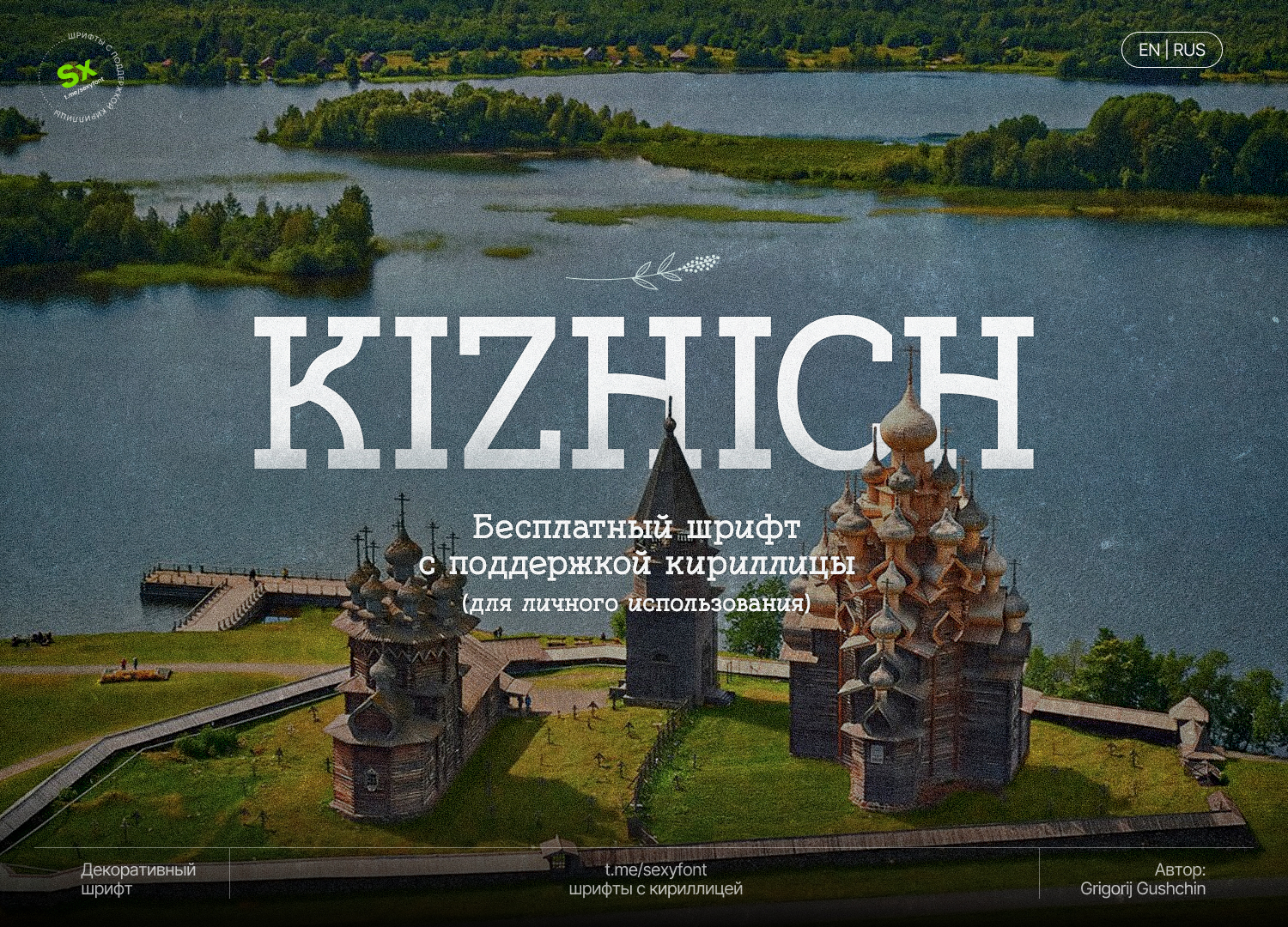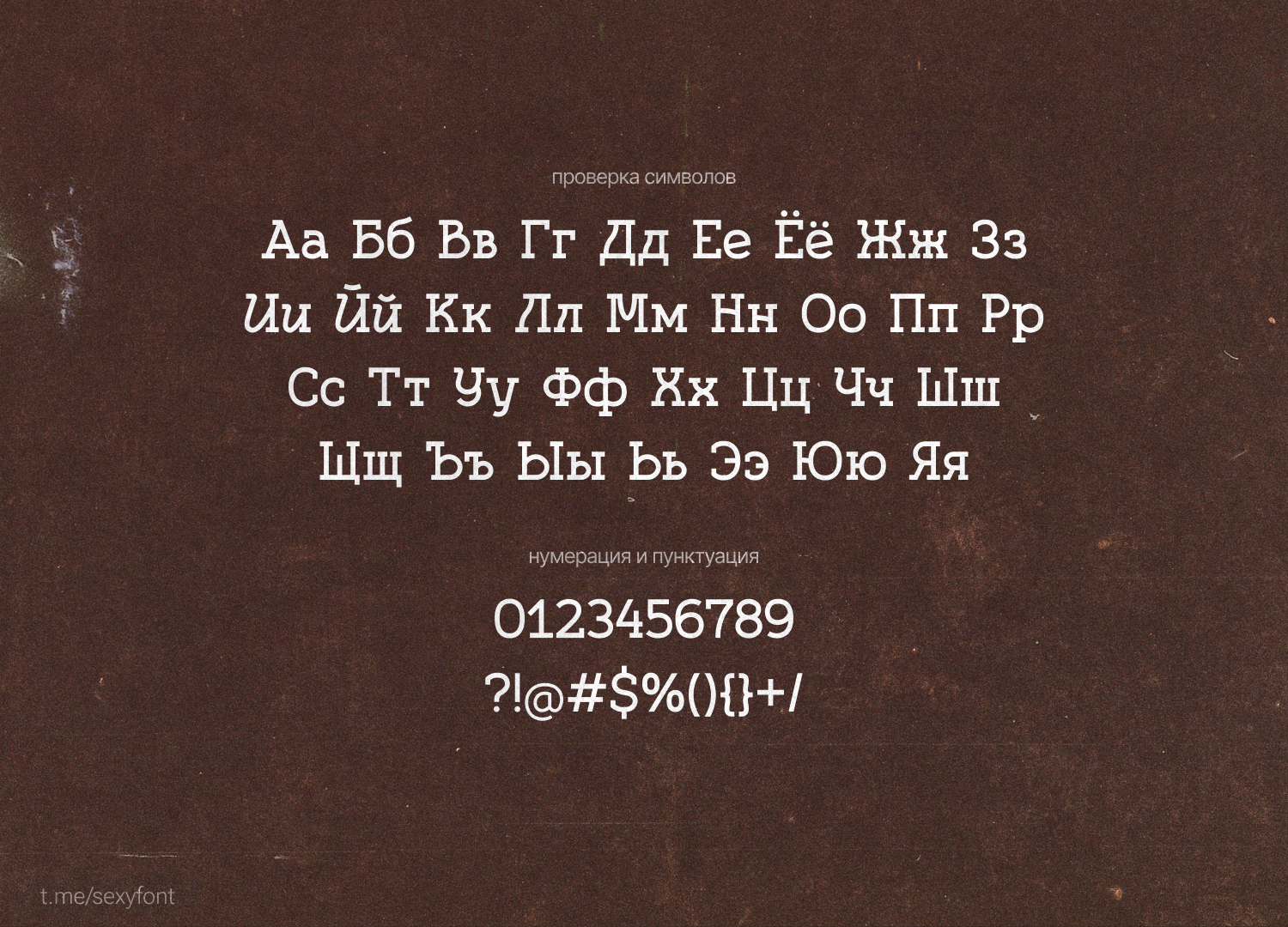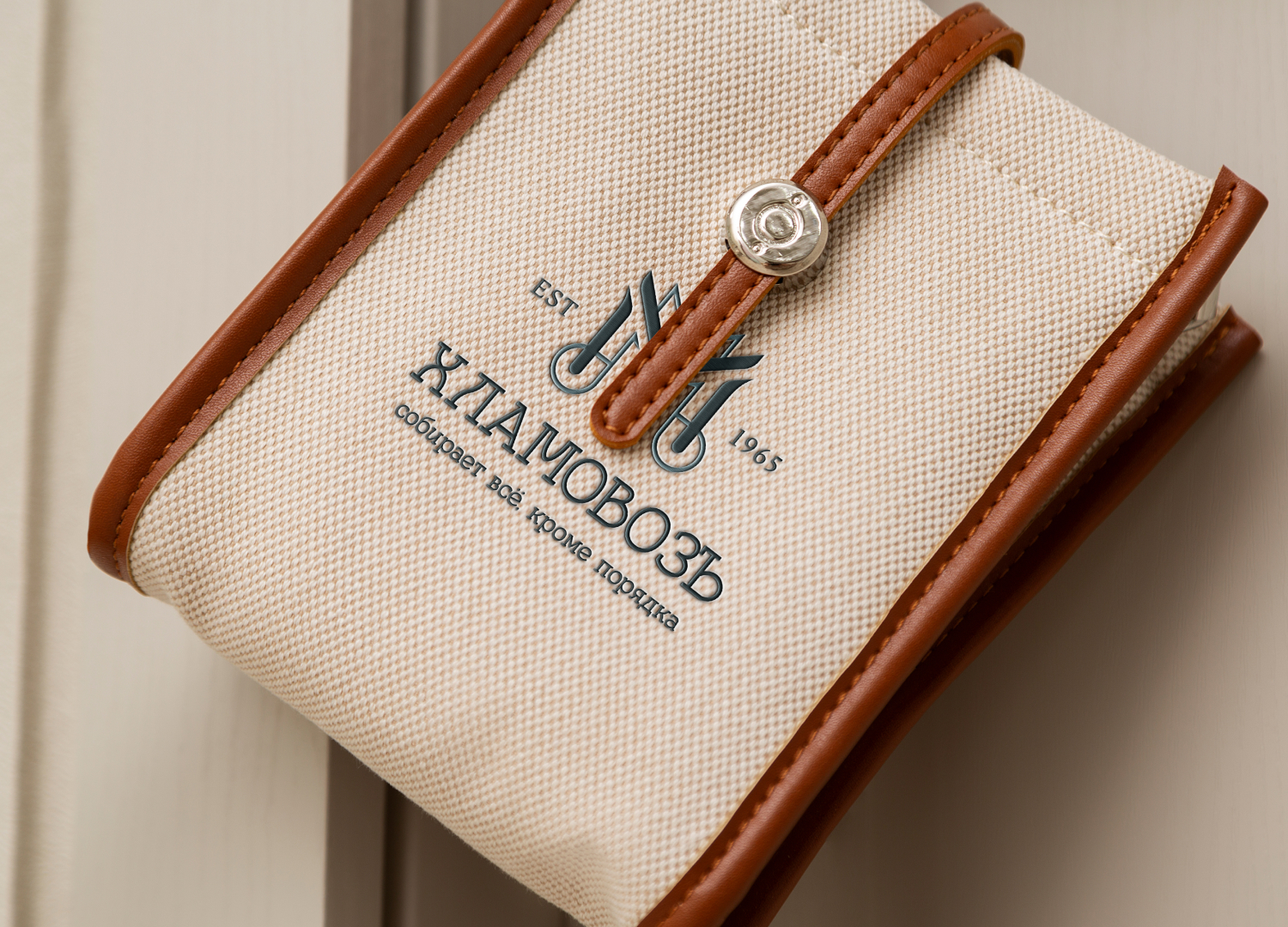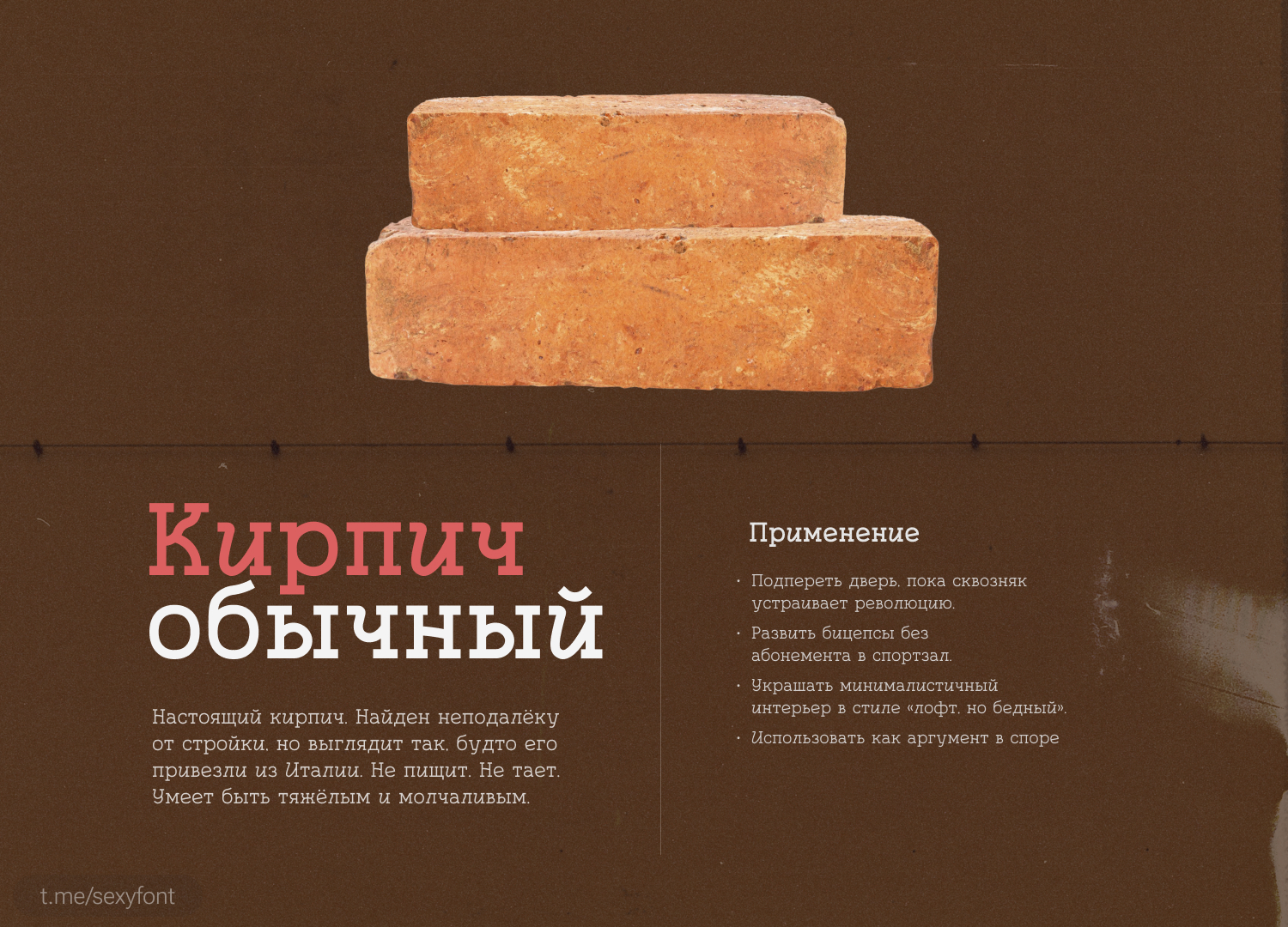
Шрифт GG Kizhich (Кижич)
Доделал новую презентацию) Шрифт GG Kizhich — брутальный декоративный шрифт с поддержкой кириллицы.Будто вырезан по дереву или выдолблен в камне: массивный, выразительный, цепляет взгляд. Отлично подойдёт для афиш, постеров, логотипов и заголовков, где нужен акцент и характер. Автор: Grigorij Gushchin